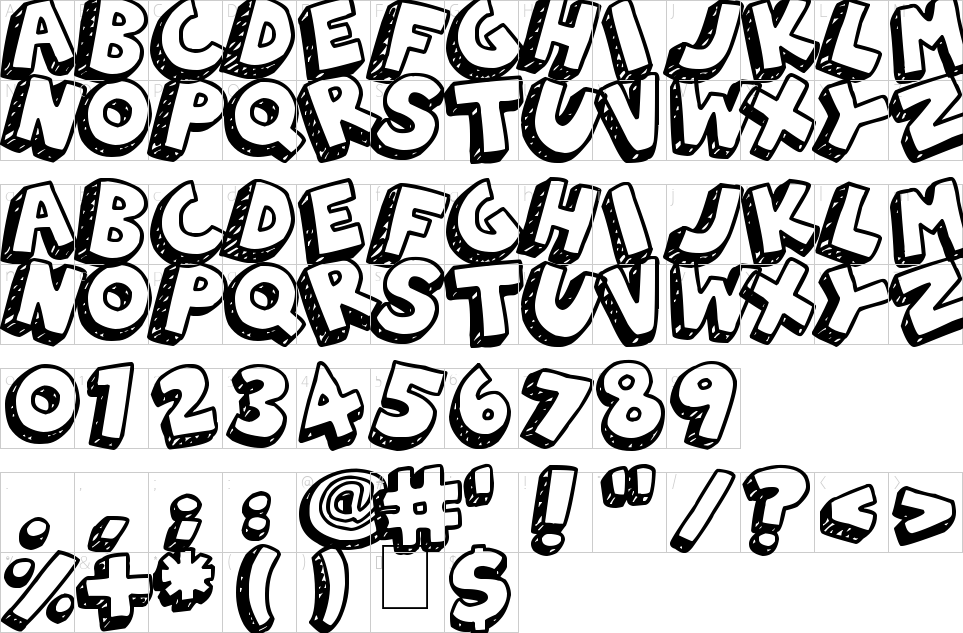
Aqui está uma descrição em português do Brasil para a página de download da fonte ‘3D Hand Drawns Font | 1001 Free Fonts’, seguindo as regras fornecidas: A fonte ‘3D Hand Drawns Font’ é um recurso gratuito e fantástico para designers gráficos e amadores. Desenvolvida pelo designer desconhecido Darrell Flood, esta fonte traz um toque único e autêntico à sua produção de design. Ela captura a essência de um desenho a mão, mas com uma pegada 3D que deixa qualquer projeto que use-a imediatamente memorável e moderno. Esta fonte é perfeita para designers que buscam dar um toque especial a textos em seus projetos, adicionando um toque artesanal sem precisar recorrer a desenhos originais. ‘3D Hand Drawns Font’ é uma opção incrível para quem busca uma fonte que combine a elegância clássica da escrita a mão com a modernidade de um visual 3D, tudo sem ter que pagar por isso. Sua versatilidade e facilidade de uso tornam-na uma fonte indispensável para qualquer designer buscando trazer um toque especial ao seu trabalho.